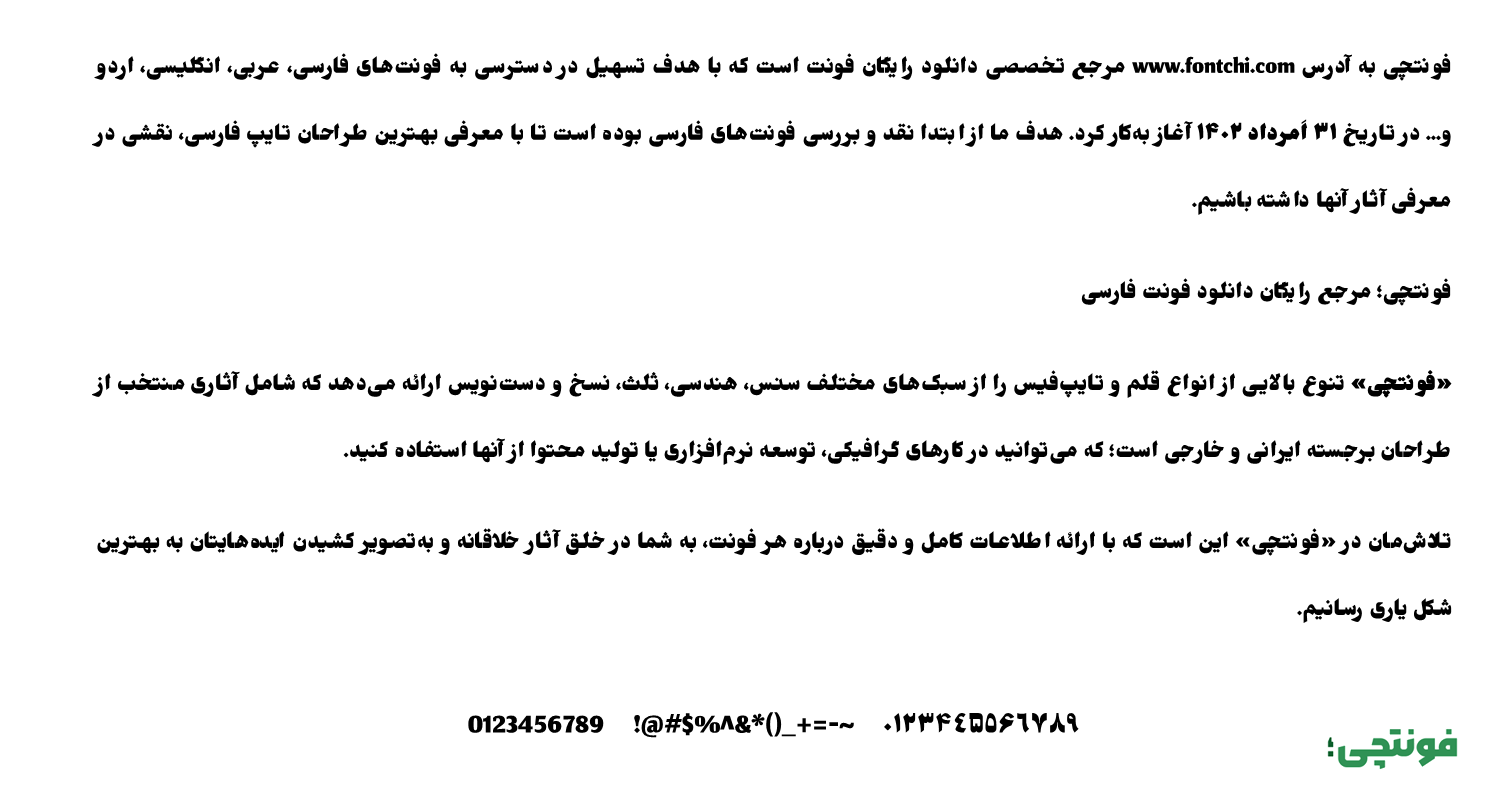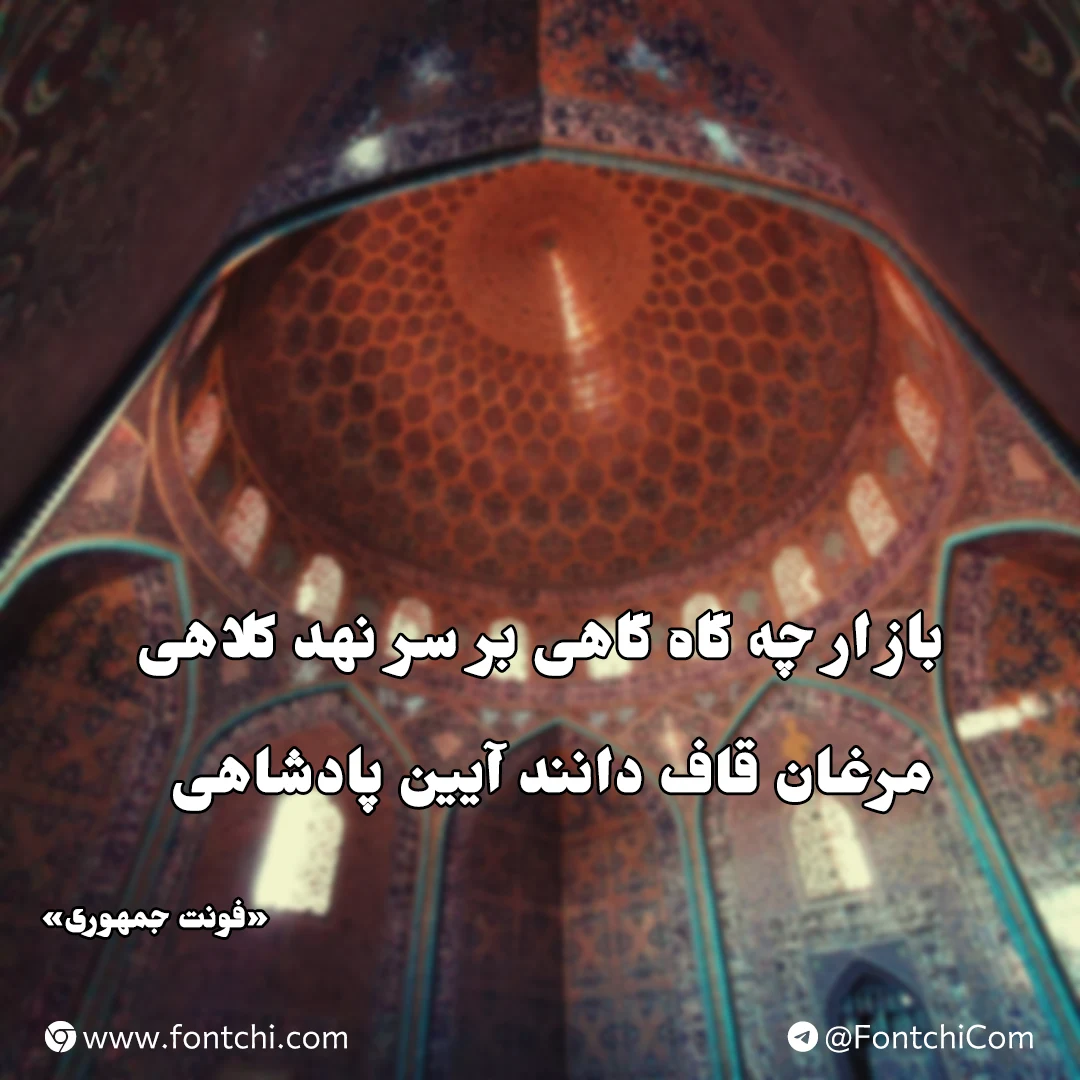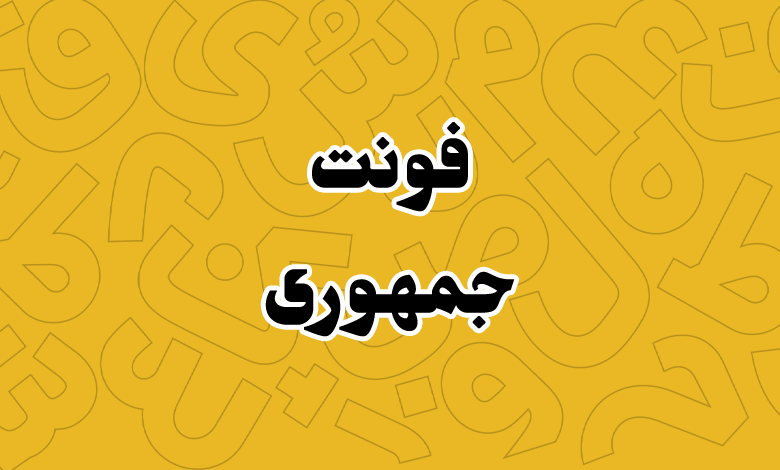
فونت جمهوری (Jomhuri)
فونت جمهوری (به انگلیسی: Jomhuri) توسط کوروش بیگپور و تیم KB Studio، در دسته فونتهای نمایشی فارسی طراحی شده است. این فونت برای استفاده در کارهای گرافیکی، پوسترها، تیترها و پروژههای بصری با تمهای مدرن و جسورانه مناسب است.
در طراحی این فونت بولد فارسی از سبکهای تایپوگرافی معاصر و در عین حال ریشهدار خط فارسی الهام گرفته شده که توانسته جایگاه ویژهای در میان طراحان گرافیک و تایپوگرافان ایرانی پیدا کند.
فونت جمهوری یک فونت سنسسریف (Sans-Serif) است که با خطوط صاف، هندسی و ضخامت یکنواخت، ولی با ظاهر نمایشب خود، ساختاری مدرن و مینیمال ارائه میدهد. این فونت در یک وزن معمولی اما با ساختار بولد عرضه شده است که انعطافپذیری بالایی برای استفاده در پروژههای متنوع فراهم میکند. ویژگیهای کلیدی آن عبارتند از:
- خوانایی بالا در اندازههای بزرگ: فونت جمهوری به دلیل طراحی درشت و قوی، برای تیترها، لوگوتایپها و عناوین مانند تبلیغات یا جلد کتاب بسیار مناسب است.
- ساختار هندسی: خطوط منظم و زوایای دقیق این فونت، حس حرفهای و مدرن را به طرحها منتقل میکند. برشهای جزئی در بخشهای مختلف حروف نیز ساختار آن را نمایشی کرده است.
- پشتیبانی از حروف و اعداد فارسی: این فونت بهخوبی با نیازهای تایپوگرافی فارسی هماهنگ شده و از ترکیبات حروفی روان و یکپارچه پشتیبانی میکند.
- ظاهر نمایشی: به دلیل ضخامت و استایل خاص، این فونت بیشتر برای کاربردهای نمایشی مناسب است تا متون طولانی.
فونت رایگان جمهوری از زبانهای فارسی و عربی پشتیبانی میکند. در این دو زبان میتوانید از گلیف استاندارد حروف، اعداد و اعراب خاص استفاده کنید. اعدادی همچون «۴۵۶» عربی در این فونت دارای گلیف استاندارد خود بوده و نسبت به اعداد «۴۵۶» فارسی ظاهر متفاوت خود را دارند.
برای زبانهای لاتین این فونت فاقد گلیفهای اختصاصی بوده و از فونت دیگری با وزن بولد که متناسب با ساختار این تایپفیس است وام گرفته شده است.
از جمله کاربردهای این فونت میتوان به طراحی پوسترهای تبلیغاتی و فرهنگی، لوگوتایپ و برندینگ، تیترهای مجلات و نشریات، پروژههای دیجیتال مانند بنرهای وبسایت و پست شبکههای اجتماعی، بستهبندی محصولات و… اشاره کرد.